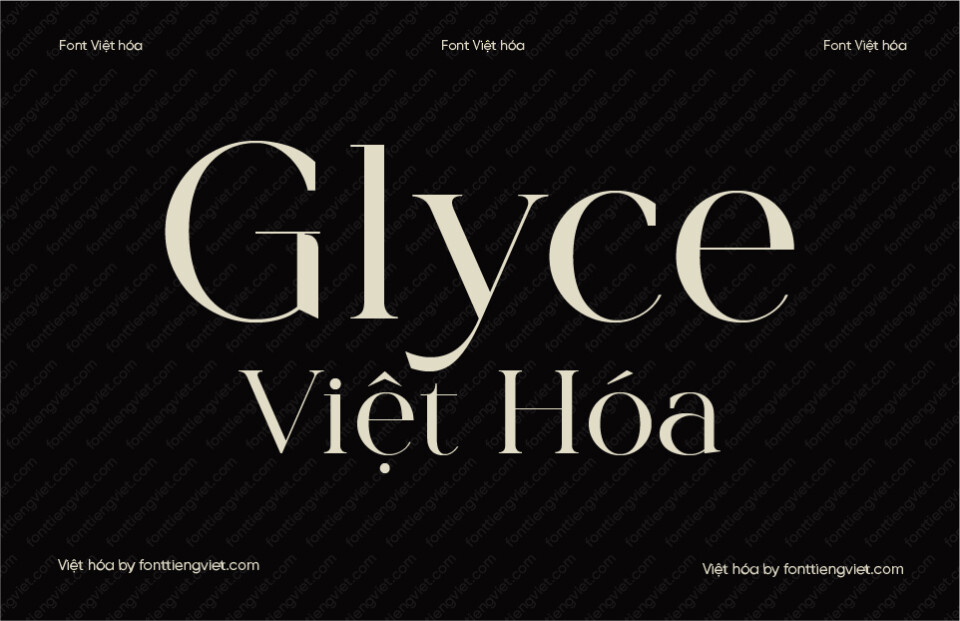
Font Việt hóa 1FTV VIP Glyce
Trong thế giới thiết kế đồ họa hiện đại, việc tìm kiếm một bộ chữ vừa mang nét phá cách độc đáo vừa hỗ trợ đầy đủ tiếng Việt là ưu tiên hàng đầu của nhiều nhà sáng tạo trẻ. Font Việt hóa 1FTV VIP Glyce chính là câu trả lời hoàn hảo cho những ai đang tìm kiếm sự khác biệt và đẳng cấp trong từng nét vẽ. Đây là một bộ Font Miễn Phí được tinh chỉnh vô cùng tỉ mỉ, giúp người dùng dễ dàng truyền tải thông điệp một cách ấn tượng nhất trên mọi nền tảng số. Với sự kết hợp giữa nét chữ hiện đại và khả năng hiển thị mượt mà, bộ font này đang nhanh chóng trở thành xu hướng mới trong cộng đồng thiết kế tại Việt Nam, đặc biệt là trong các dự án đòi hỏi tính thẩm mỹ cao.
Khám phá sức hút đặc biệt của Font Việt hóa 1FTV VIP Glyce
Bộ font này không chỉ đơn thuần là các ký tự văn bản mà còn là một tác phẩm nghệ thuật hình học đầy tinh tế. Điểm nổi bật nhất của Font Việt hóa 1FTV VIP Glyce nằm ở cấu trúc các đường nét thanh mảnh nhưng vô cùng chắc chắn, tạo cảm giác chuyên nghiệp và sang trọng cho người xem. Các dấu câu tiếng Việt được đội ngũ 1FTV xử lý cực kỳ khéo léo, đảm bảo không bị lỗi font hay mất đi sự cân đối vốn có của thiết kế gốc. Điều này giúp các bạn học sinh và sinh viên dễ dàng ứng dụng vào các bài thuyết trình PowerPoint hoặc làm bìa báo cáo mà không lo ngại về vấn đề hiển thị.
Ứng dụng đa dạng trong các dự án thiết kế
Nhờ phong cách tối giản nhưng không kém phần nổi bật, Font Việt hóa 1FTV VIP Glyce cực kỳ phù hợp cho các thiết kế thương hiệu như logo, danh thiếp hay tiêu đề poster phim. Trong lĩnh vực truyền thông mạng xã hội, bộ font này giúp các hình ảnh quảng cáo trở nên bắt mắt hơn, thu hút sự chú ý của khách hàng ngay từ cái nhìn đầu tiên. Ngoài ra, tính ứng dụng của nó còn mở rộng sang mảng UI/UX, giúp giao diện ứng dụng di động trở nên thanh thoát và dễ đọc hơn đối với người dùng cuối.
Hướng dẫn sử dụng Font Việt hóa 1FTV VIP Glyce hiệu quả
Để phát huy tối đa vẻ đẹp của bộ chữ này, bạn nên kết hợp nó với những tông màu tương phản mạnh hoặc các phông nền tối giản. Việc sử dụng Font Việt hóa 1FTV VIP Glyce làm tiêu đề chính (Heading) kết hợp với một font không chân (Sans-serif) đơn giản cho phần nội dung sẽ tạo nên một bố cục phân cấp thị giác rõ ràng. Đừng ngần ngại điều chỉnh khoảng cách giữa các chữ cái (kerning) để tạo ra những hiệu ứng thị giác mới lạ, phù hợp với tinh thần của từng tác phẩm cụ thể mà bạn đang thực hiện.
Kết luận về bộ Font Việt hóa 1FTV VIP Glyce
Sở hữu Font Việt hóa 1FTV VIP Glyce trong bộ sưu tập của mình sẽ giúp bạn tiết kiệm đáng kể thời gian trong việc tìm kiếm giải pháp kiểu chữ phù hợp. Với sự tỉ mỉ trong quá trình việt hóa và phong cách thiết kế thời thượng, đây chắc chắn là một công cụ hỗ trợ đắc lực cho mọi nhà thiết kế từ nghiệp dư đến chuyên nghiệp. Hãy cùng trải nghiệm và lan tỏa tinh thần sáng tạo Việt cùng Font Miễn Phí, Font Việt Hóa, Font Việt hóa 1FTV VIP Glyce ngay hôm nay để nâng tầm những sản phẩm đồ họa của chính mình trong tương lai gần.